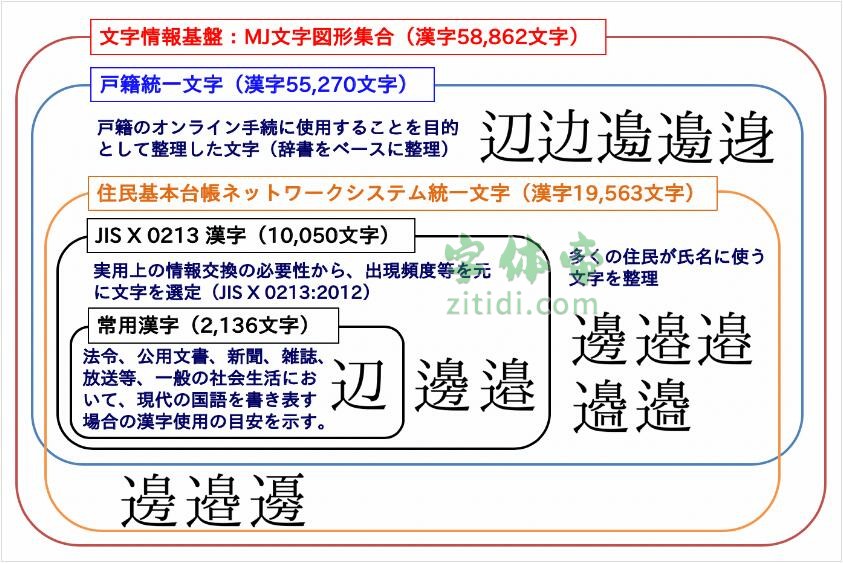
IPAmj明朝体字体信息
IPAmj明朝体
字体名称: IPAmj明朝体
字体风格: 明朝体
IPAmj明朝体是日本IPA独立行政法人情报处理推进机构推出的一款字体,这是日本的一个关于文字信息基础建设事业的网站。IPA文字信息基础建设事业,是根据日本平成22年电子经济产业省推进计划(关于文字信息基础构建的研究开发事业)启动的,主要是对日本使用的约6万个汉字进行分类整理标准化项目。这个项目公开了《文字信息基础文字一览表》和《IPAmj明朝体》,是为了普及促进和国际标准化的活动。